“Avatar”, la millonaria película que usa fuente de Word: ¿qué dijo James Cameron 13 años después?
Conoce la historia de Papyrus, la polémica tipografía que provocó que hasta Ryan Gosling “se burlara” del director y la película.
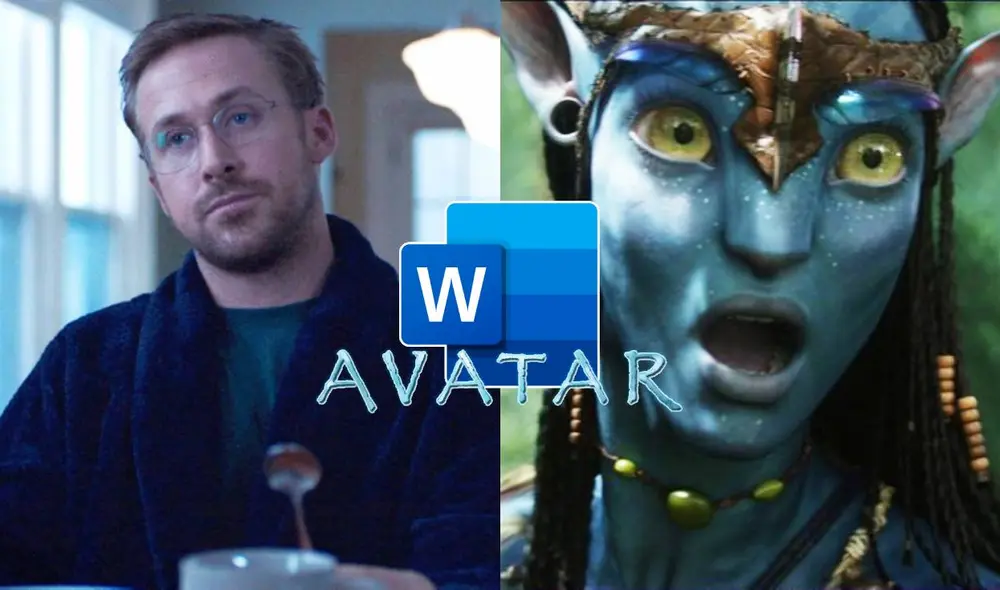
“Avatar: el camino del agua” ha tomado 13 años para poder estrenarse en cines y ahora solo estamos a unos días de poder presenciarla en la pantalla grande. Pero lejos de su polémico tiempo de desarrollo y su duración de tres horas, existió otro tema que también generó controversia: el uso de una fuente predeterminada de Word en su logotipo. ¿Cuál es la historia detrás y qué dijo James Cameron 13 años después?
Papyrus, la obsesión de Ryan Gosling
Tras el éxito que tuvo la primera cinta sobre el mundo de Pandora en 2009, pasó un tiempo hasta que alguien notara una curiosidad: la tipografía del logotipo de “Avatar” era una llamada Papyrus y cualquiera que tuviese Microsoft Word podía emularla fácilmente.
El descubrimiento lo hizo “Saturday night live”, que lanzó un cortometraje protagonizado por Ryan Gosling en el que se burlaba del uso de esta fuente predeterminada en uno de los programas más usados del mundo.
En el corto, el personaje de Ryan vive indignado y obsesionado con el logotipo del filme y cree que se trata de un acto de pereza por parte del diseñador, por lo que va en busca de él para confrontarlo.
La fuente Payrus aún puede encontrarse en las versiones más recientes de Microsoft Word. Foto: captura de Youtube/SNL
La ocurrente ficción no solo desató los comentarios en redes sociales al punto de volverla una broma recurrente sobre la película, sino que también llevó al responsable del diseño a aclarar el asunto en cuestión.
La respuesta de Cameron 13 años después
Luego de 13 años, “Avatar: el camino del agua” ya tiene otro logotipo, pero James Cameron no ha dejado pasar la oportunidad para al fin hablar sobre Papyrus.
Logotipos de "Avatar" para su primera y segunda película. Foto: composición/Disney
“No sabía que nuestra fuente era algo estándar. Asumí que el Departamento de Arte o la compañía de títulos la inventaron. Por supuesto, fue criticada sin piedad como una elección perezosa, pero, francamente, me gusta la fuente”, explicó.
Asimismo, señaló que “si Papyrus resuena con los problemas de las culturas indígenas en la conciencia pública, entonces eso encaja bien con ‘Avatar’, así que no estoy dejando de dormir por eso”.
El origen bíblico del logotipo de “Avatar”
Chris Cotello, el responsable del uso de Papyrus en el logotipo de “Avatar”, habló sobre dicha parodia con CBS News el mismo año en el que la parodia de SNL salió al aire y admitió que había estallado de risa al verla con su esposa.
“Diseñé la fuente cuando tenía 23 años. Salí de la universidad y tenía diversos problemas, estaba estudiando la Biblia, buscando a Dios y esta fuente llegó a mi mente”, señaló.